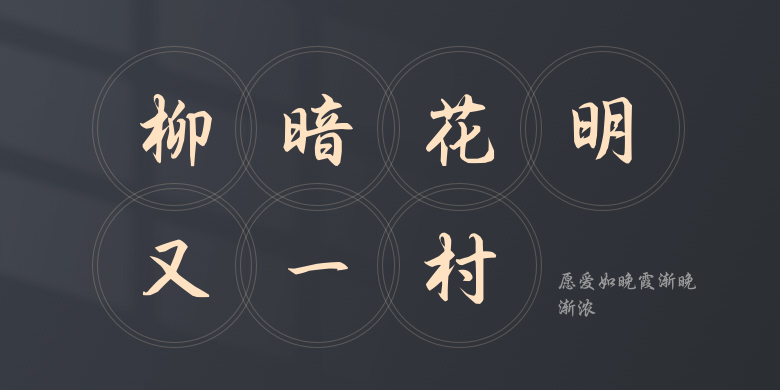
愿爱如晚霞渐晚渐浓
愿爱如晚霞渐晚渐浓,这款字体结构工整、笔画清晰,兼顾美观与易读性,适用于标题、正文、海报、包装、LOGO 等多种场景。字形优雅稳定,风格百搭耐看,适配日常排版与创意设计,让文字呈现更舒适、更具质感。愿爱如晚霞渐晚渐浓一笔一画,皆是细节,以均衡的比例、流畅的线条打造舒适视觉体验,字形端正大气,风格简约现代。无论是商业设计、品牌宣传还是日常排版,都能轻松驾驭,让文字更有格调与力量。愿爱如晚霞渐晚渐浓字体下载。